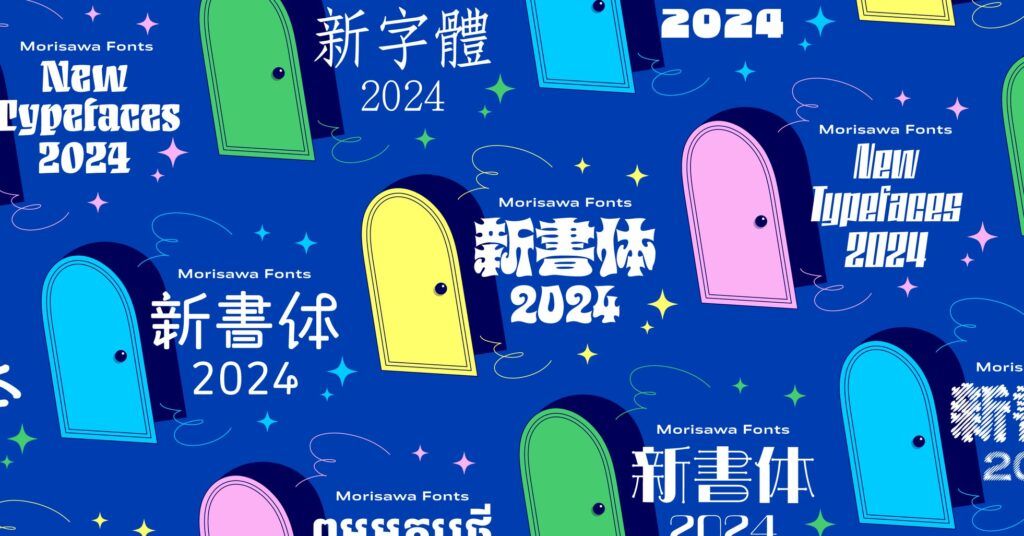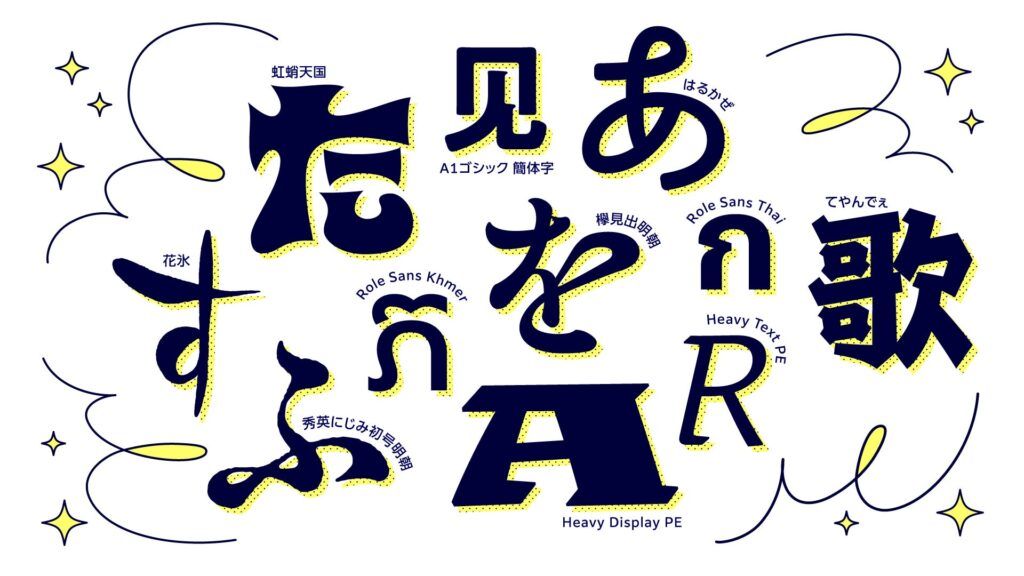
モリサワ 2024年度新書体として140以上のデザインをリリース、新書体ティザーサイトもオープン
株式会社モリサワは、2024年度新書体として、すでに発表済みの写研フォントや当社初の和文バリアブルフォント「DriveFlux」に加えて、世界観づくりにぴったりな和文デザイン書体やグローバルな情報発信にも対応できる多言語書体など、合わせて140以上のファミリーをリリースする。
このほど、追加ラインナップ発表に合わせ、新書体ティザーサイトを公開しました。サイト内では、ラインナップや書体見本をまとめた紹介ムービーを掲載した。
2024年度新書体は、サイケデリックなアートや音楽からインスパイアされた極太の「虹蛸天国(にじたこてんごく)」のほか、丸い輪のような装飾が楽しげな印象を与える「はるかぜ」、江戸文字からインスパイアされた「てやんでぇ」など、世界観づくりにぴったりなデザイン書体をリリース。
さらに書家による毛筆の文字が元となった「花氷(はなごおり)」など、華やかな筆文字系デザイン書体の選択肢が広がる。明朝体には、2023年にリリースした「欅(けやき)明朝 Oldstyle」の見出し書体「欅見出明朝」や、人気の「秀英にじみ」シリーズから「秀英にじみ初号明朝」などを新たに追加したほか、ユニークなファミリー展開が特徴の「Heavy」シリーズなど、デザインに彩りを加える特色豊かな欧文書体にも注目されている。
そのほか、グローバルな情報発信にも対応できる多言語フォントが拡充し、オールドスタイルのゴシック体「A1ゴシック」に簡体字や繁体字が、欧文スーパーファミリー「Role」にインドと東南アジアの主要な種類の文字に対応する多言語展開ファミリーが登場した。